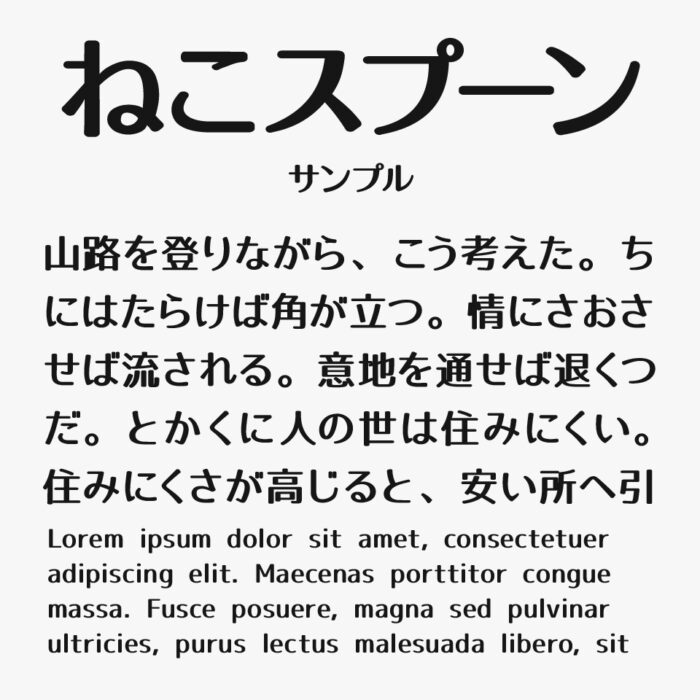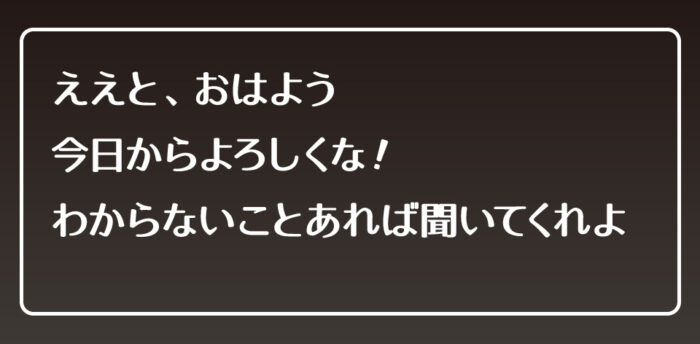
ねこスプーンフォントは、ロゴたいぷゴシックフォントをベースに独自に調整されたゲーム向けに制作されたタイポス系フォントです。
ひらがなやカタカナの線がふっくらと太めに見え、どこか「ぬくもり」や「親しみ」を感じさせます。可愛すぎず、クールすぎないぐらいのバランス感のフォントです。
ゲーム上のテキストとして意識して制作されているので、インディーズゲームなどを制作されている方にもぴったりなフォントです。
| 漢字 | ○(教育漢字・常用漢字・第一〜二水準漢字) |